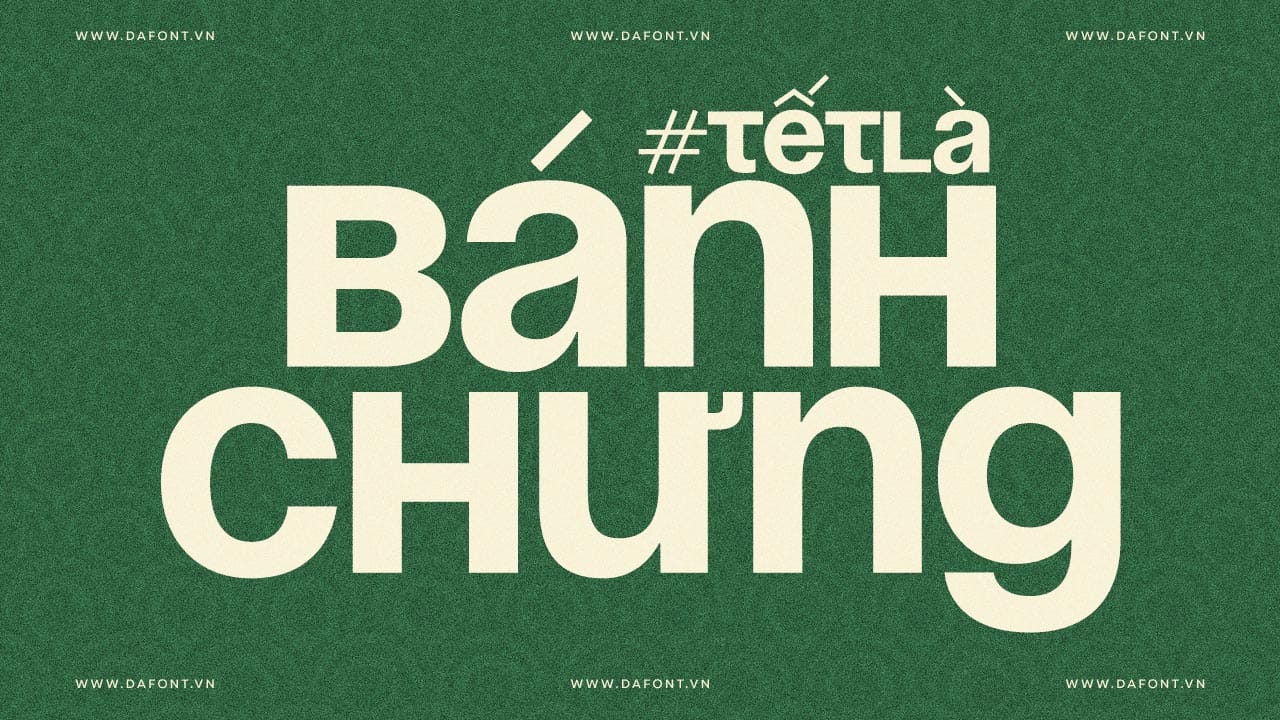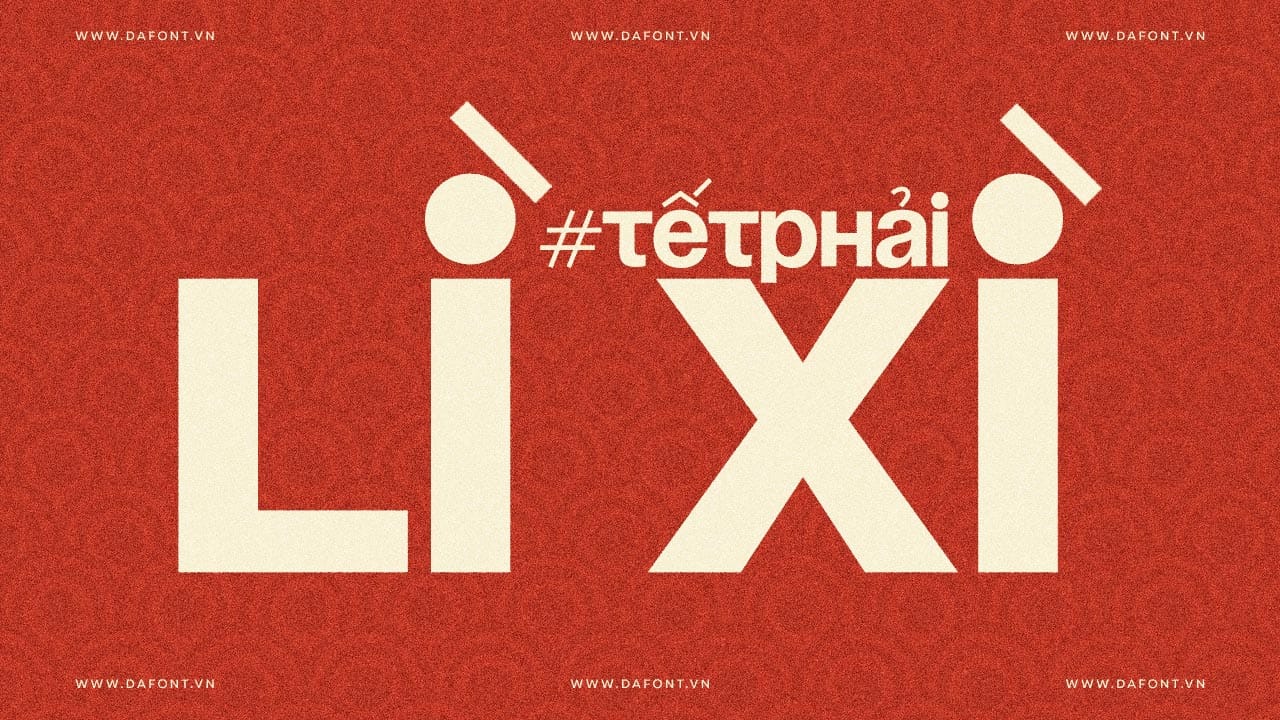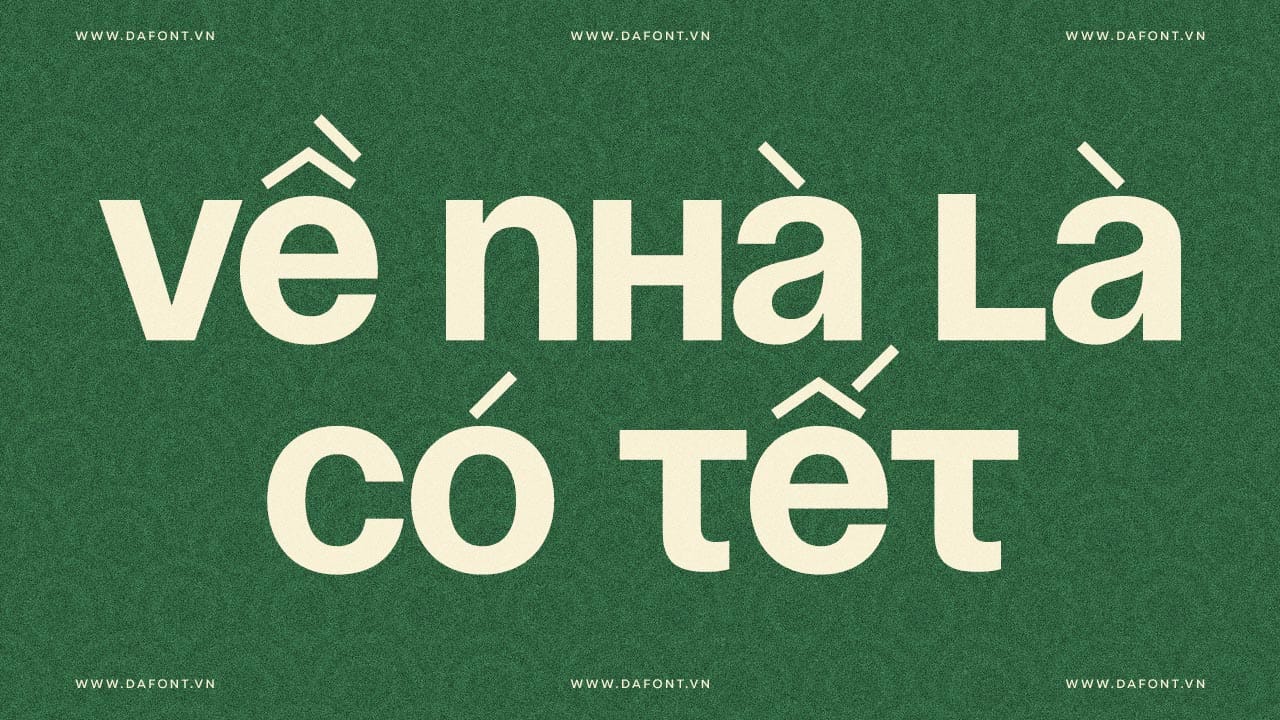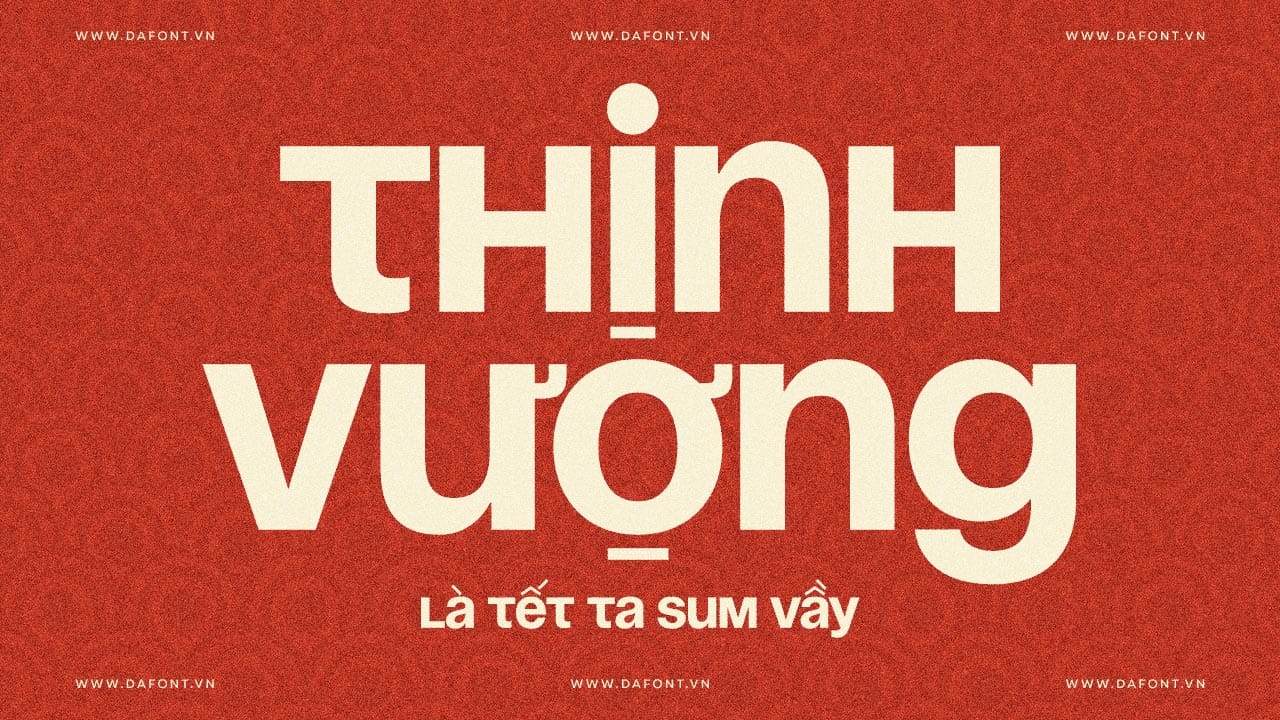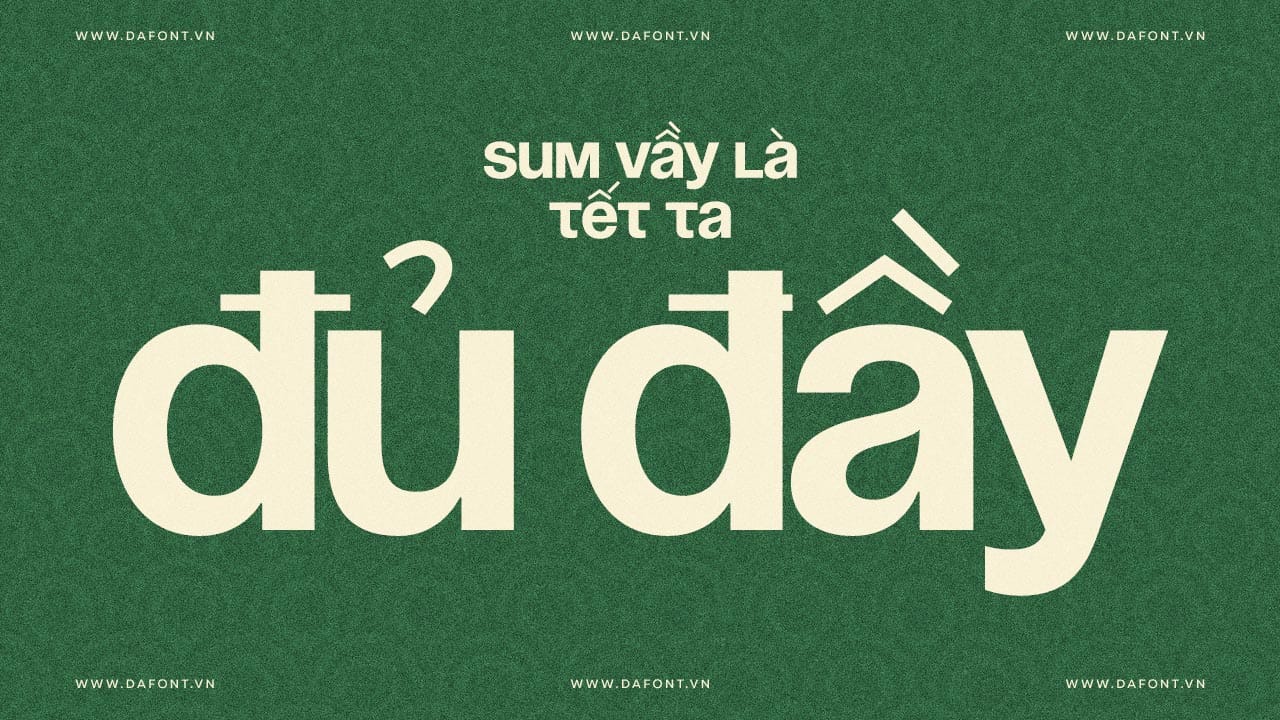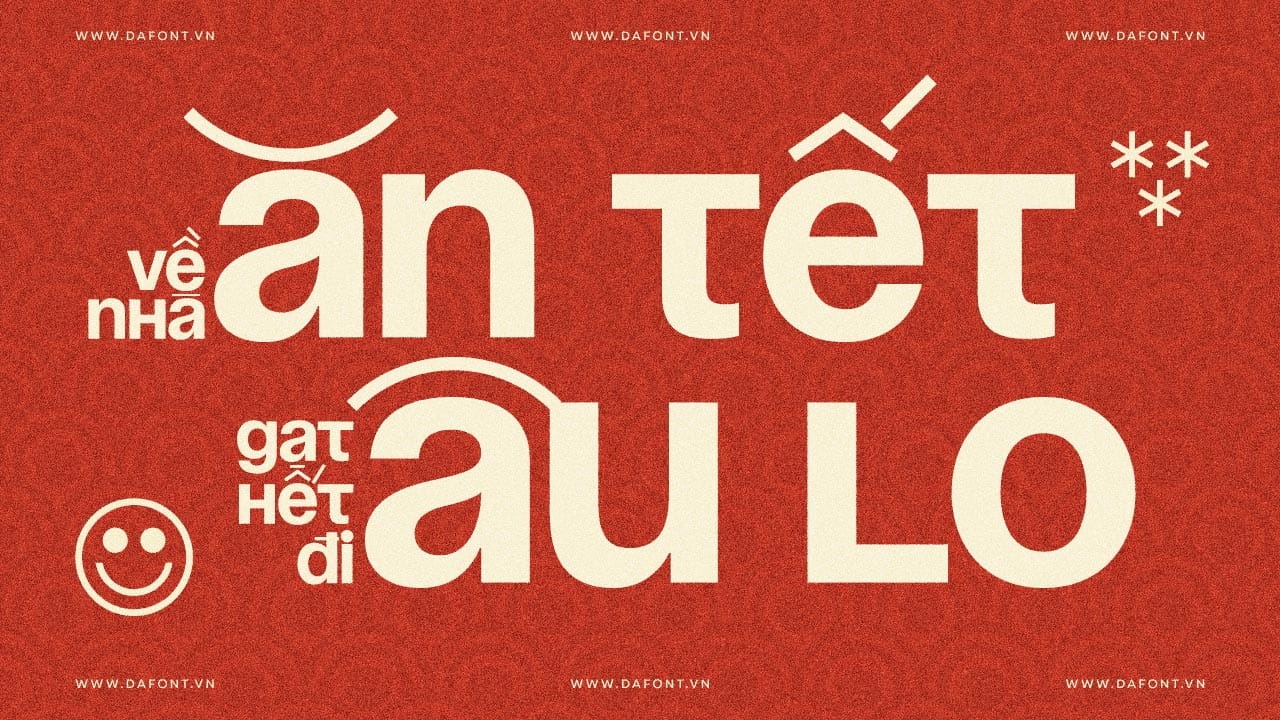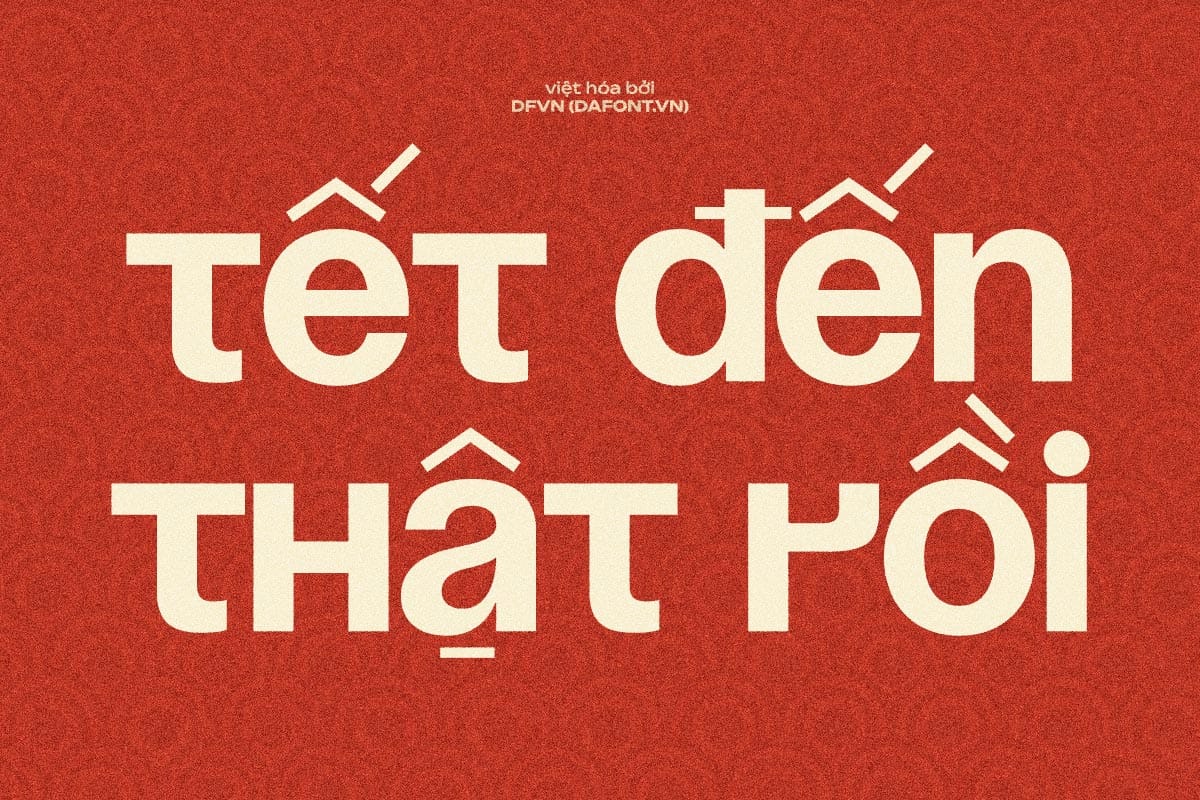
Font Tết Tết Tết – DFVN Soyuz Grotesk Việt hóa v2.0 – Phiên bản nâng cấp hoàn thiện từ DFVN, nâng cấp glyph, tối ưu kerning.
Soyuz Grotesk là một trong những font sans-serif hiện đại, mạnh mẽ và dễ ứng dụng. Với phong cách tối giản, bố cục chữ cân đối và Việt hóa hoàn chỉnh, font này trở thành lựa chọn lý tưởng cho những nhà thiết kế yêu thích sự tinh gọn nhưng vẫn nổi bật.
Soyuz Grotesk là một kiểu chữ grotesk hiện đại với form chữ khỏe khoắn, đường nét dứt khoát và khả năng hiển thị rõ ràng, đặc biệt phù hợp cho tiêu đề, poster, thiết kế thương hiệu, giao diện số, banner, thiết kế mùa lễ Tết và các ấn phẩm truyền thông.
Phiên bản Việt hóa Soyuz Grotesk v2.0 được tinh chỉnh mượt mà, đảm bảo đầy đủ dấu và ký tự tiếng Việt, giúp font trở thành lựa chọn nổi bật cho những dự án cần sự mạnh mẽ, tối giản và mang tính nhận diện cao.